La gran cita del fútbol mundial se va acercando y las grandes marcas de presentado las que serán las equiparaciones para los diferentes países que competirán en el mundial de fútbol de Brasil. Nike con 10 equiparaciones es la marca que mas selecciones vestirá, seguida de Adidas y Puma que vestirán 8, y el resto de equiparaciones las proporcionaran Joma, Lotto, Marathon, Legea, Burrda Sport y Uhlsport.
Como ya hicimos con la equipación del Real Madrid para la presente liga o para la del Barcelona C.F de la pasada temporada, en Lettering Time vamos hacer un repaso al diseño de algunas de estas equiparaciones y como ya habrás adivinado vamos hacer especial hincapié en las tipografías que se utilizan en ellas.
Voy a empezar por la equipación de la selección de Inglaterra y el motivo es el diseñador por el que han apostado para llevarla a cabo, Neville Brody.
El propio Brody comenta que el diseño de la tipografía combina un toque sutil de industria que le da el uso de una tipografía stencil con el aire moderno que le ofrece los motivos a rayas de la camiseta. Eficacia y estilo sin lujos dice Brody.
Por su parte Holanda se ha inspirado en los diseños y tipografías de su compatriota Wim Crouwel para darle a la tipografia de sus camisetas un aspecto retro.
Nike comenta que las lineas interiores de la tipografía son una reminiscencia a la mítica naranja mecánica de los años 70. De esta tipografía me ha llamado la atención el uso de ligaduras de espacio como el caso de la ligadura "ei" ( "IJ", podéis ver la información al respecto de esta ligadura que nos proporciona Rubén Prol en los comentarios) de Sneijder que podéis ver en la foto, algo no muy normal en estos usos.
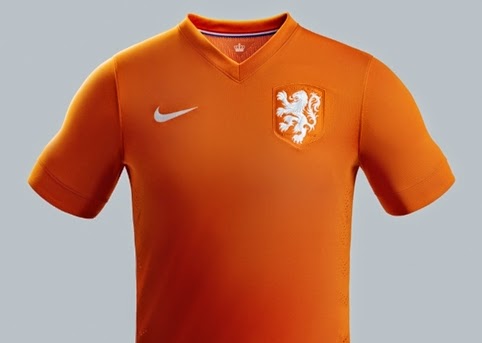
Adidas no parece haberse calentando tanto la cabeza a la hora de elegir una tipografía para cada una de las selecciones nacionales que viste ya que, si se confirma, todas las naciones que viste esta marca llevaran la misma fuente a la espalda. Una tipografía de palo seco, bastante condensada y con una gran altura de "x" que se combinará con unos números con un efecto de sombra a modo de pliegues.
Se puede discutir las tipografías elegidas por Nike en cuanto si nos parecen adecuadas o no pero lo que si que es obvio es que al menos en el caso de Nike se ve un estudio a la hora de elegir o diseñar una tipografía o otra para cada nación, en cambio Adidas parece haber dicho "venga una para todos y a correr".